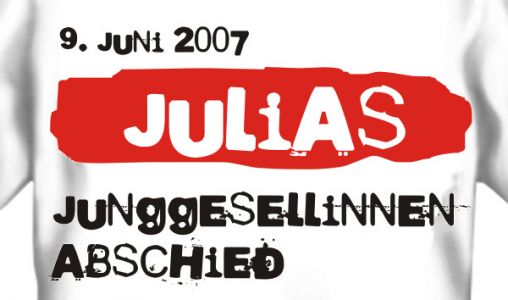
T-Shirt Druck - Schriftart unbekannt
meine schwester möchte dass ich für sie ein motiv mit einer speziellen schriftart erstelle. als beispiel hat sie mir ein bild von einer website geschickt, die t-shirts mit diversen druckmotiven verkauft bzw. speziell für den kunden erstellt. ( quelle )
ich möchte keinerlei kommerz daraus schlagen, sondern lediglich GENAU diesen font haben, weil es eine heidenarbeit wäre die ganzen buchstaben einzeln nachzusetzen - und das bloß wegen einer feier, bei der ich nicht mal dabei bin :roll:
ich nehme einfach mal an dass es sich dabei um einen font handeln muss. es ist für mich schwer vorstellbar, dass die buchstaben einzeln gesetzt und bearbeitet wurden (mit diesen strichen und klecksen usw.)... oder?
wenns nach mir ginge, hätt ich das auch gleich mit nem anderen font gemacht, aber weil meine schwester meinte ich könnte ja mal in nem forum nachfragen, eventuell wäre ja was möglich usw. usw. ...
ich lasse nichts unversucht, habe meine schwester vorhin aber auch schon gesagt, dass es mit nem anderen font auch gehen würde und sie sich besser darauf einstellt.
nebenbei: ich find den font trotzdem sehr interessant, weil ich noch nie so einen buchstabenmix erlebt hab, ein bisschen reizt es mich schon zu wissen ob das nun manuell erstellt wurde oder eben was vorgefertigtes is...
dein beipsiel ist sicher ein font.
das sieht man doch an den buchstaben die sich wiederholen.
'gg', 'NN', 'EE' usw. alles gleich. kein ps-effekt. und wenns handmade ist,
war einer faul. :P
naja, die können ja auch ein g erstellen und dass daneben duplizieren, usw.
(und für weitere verwendungen eben abspeichern)
wär aber schön wenn jemand den namen des fonts wüsste... aber wahrscheinlich ists kein freefont...
> naja, die können ja auch ein g erstellen und dass daneben duplizieren, usw.
wie gesagt:
wenn handmade, dann wars ein fauler.
aber ich denke es ist ein font. zumal die buchstaben alle auf einer linie stehen.
wer macht den sowas, wenn es nach trash aussehen soll?